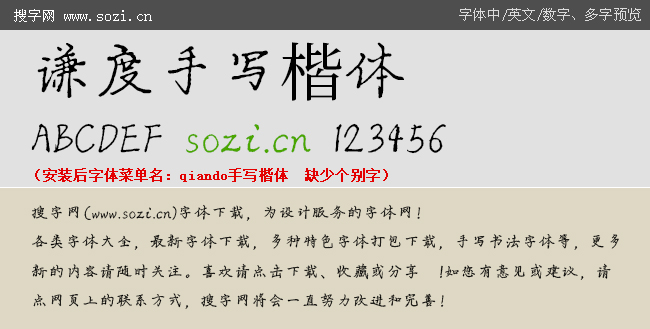
謙度手寫楷體
搜字網(wǎng)給大家提供一款謙度手寫楷體(非商業(yè)使用)中文字體下載,謙度手寫楷體是一款十分接地氣的手寫字體,字體跟我們平時(shí)用圓珠筆寫出來的一樣。而字體寫得也比較漂亮,干凈整潔。適用于個(gè)性海報(bào)、書籍裝幀、包裝設(shè)計(jì)等場(chǎng)景。